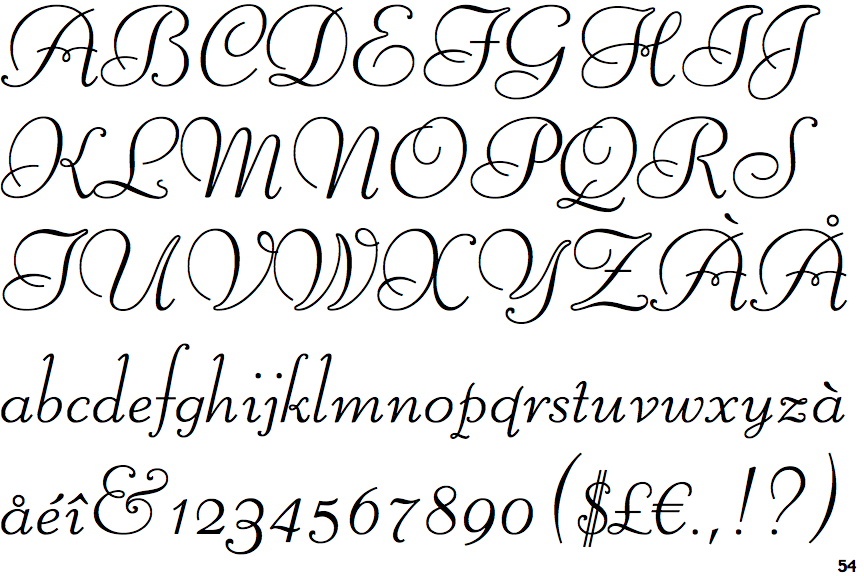
Рукописный шрифт русский от руки. Бесплатные рукописные шрифты для скачивания
Почерк, как умение рисовать, — своего рода искусство. Часто человек не может понять собственного почерка, например, при быстрой диктовке. Сегодня правильное и понятное письмо отходит на второй план, уступая место электронным документам. Но есть ситуации, когда письменная речь должна быть понятна и разборчива. Как исправить почерк и сделать его красивым, расскажет эта статья.
Примеры
Как добиться красивого почерка
Почерк относится к талантам, ведь он напрямую связан с руками. Красивое письмо — род искусства рисования. Не так давно в школах был специальный предмет, направленный на формирование четкого и красивого почерка.
Сегодня школьников уже не заставляют исписывать страницы с одним крючком, чтобы довести написание до идеала. Программа направлена на освоение навыков письма. При этом красоте и аккуратности почерка отводятся последние роли.
Но если за детьми и формированием их почерка следят родители и учителя, то как взрослому человеку научиться писать понятно и правильно? На случай если взрослый человек желает подправить или изменить почерк, существуют несколько полезных советов.
Выбор пишущего инструмента
Удобный пишущий инструмент — ключ к красивому почерку. Не так важно ручка или карандаш. Важно то, что пишущий инструмент удобно лежит в руке и позволяет пользоваться им, не напрягая руку.
Посадка при письме
Правильная посадка при работе с письмом помогает не ощущать дискомфорта. Спину нужно держать прямо, а лист, на котором пишется текст, следует расположить под удобным для написания углом.
Прописи
Главный совет по улучшению почерка — заново прописать задания в школьных прописях.
Они помогут вспомнить о правильном написании соединений между буквами и попрактиковаться в их отработке.
Практика
При выработке стиля почерка важно помнить, что постоянная практика позволит лучше запомнить правильное написание всех буквенных элементов. Важно стараться писать чаще и внимательно следить за выполнением написания. К примеру, если не получается написание отдельного элемента буквы или соединение, стоит выписать его на отдельный лист и прописывать до тех пор, пока не получится удовлетворительный результат.
Неторопливость
Не стоит ожидать, что почерк улучшится через час сидения за прописью. При работе над почерком важно делать работу вдумчиво и не торопясь. Если не нравится получившийся результат, стоит над ним поработать еще и сравнить с тем, что было ранее. Прогресс в работе может наступить как через неделю, так и через несколько месяцев.
Фантазия и шрифты
При работе над написанием стоит подключить фантазию или взять за образец понравившиеся прописные шрифты на компьютере.
Смена пишущего инструмента
После освоения одного инструмента стоит попробовать другие приспособления. Если использовалась шариковая ручка, стоит практиковать маркер или перьевую авторучку. Это важно чтобы выработанный почерк не менялся при использовании разных по своей конфигурации инструментов. Таким образом, можно отрегулировать нажим на бумагу и удобный хват для каждого типа ручки или карандаша.
Написание иностранного алфавита
Освоение прописных иностранных букв помогает при внесении правок в собственный почерк. Начать стоит с азов — английский алфавит, написанный красивым почерком, выглядит в достаточной мере похожим на русский, что помогает при проработке проблемных мест на ассоциативном уровне.
С помощью таких несложных советов можно полностью изменить свой почерк, сделав его каллиграфическим. Однако правильный почерк для школы не всегда подходит для взрослого человека.
Почерк взрослого человека несет в себе отпечаток личности и ее уникальность.
Как известно, хорошего много не бывает. Это касается и шрифтов. Красивый сбалансированный шрифт может стать украшением любого проекта. Но поиск подходящего начертания порой может занять очень много времени, особенно, если дизайнеру нужен рукописный шрифт. Такие шрифты отличаются от серифов и сан-серифов тем, что зачастую имитируют почерк дизайнера или его видение того, как должен выглядеть рукописный шрифт. Нельзя сказать, что таких шрифтов мало, напротив, их явный переизбыток. Но действительно хороших рукописных шрифтов, особенно бесплатных, не так уж много, поэтому дизайнерам приходится прочесывать множество сайтов в поисках настоящего алмаза. FreelanceToday предлагает вашему вниманию 20 бесплатных рукописных шрифтов, которые можно использовать как в личных, так и коммерческих проектах.
Рукописный шрифт King Basil, созданный дизайнером Мисси Мейер, отличается плотными штрихами, но при этом он очень мягкий и немного женственный. Шрифт бесплатный, его можно задействовать в самых разных проектах, как цифровых, так и печатных. King Basil отлично подходит для создания логотипов, им можно набирать заголовки, делать анонсы различных мероприятий.
Создательница Milkshake Лаура Уортнигтон стремилась сделать универсальный, дружественный и удобный для чтения рукописный шрифт. И ей это удалось на 100%. Шрифт получился очень удачным, в меру массивным, но не грубым. Символы гармонично перетекают, все буквы хорошо сочетаются друг с другом. Milkshake получился немного винтажным, глядя на него, почему-то вспоминается логотип Coca-Cola. Шрифт отлично подойдет для ретро-проектов, его смело можно использовать в рекламе продуктов питания или товаров для детей.
Oleo Script от Soytutype Fonts
84. PacificoСовременный каллиграфический шрифт, вдохновленный свободой серфингистов 1950-ых. Еще одно сочетание винтажа и молодежности.
Pacifico от Vernon Adams
85. ParisienneБлизкая к классической каллиграфия с широкими буквами и завитками — освободите больше пространства вокруг, чтобы они не мешали читать остальной текст.